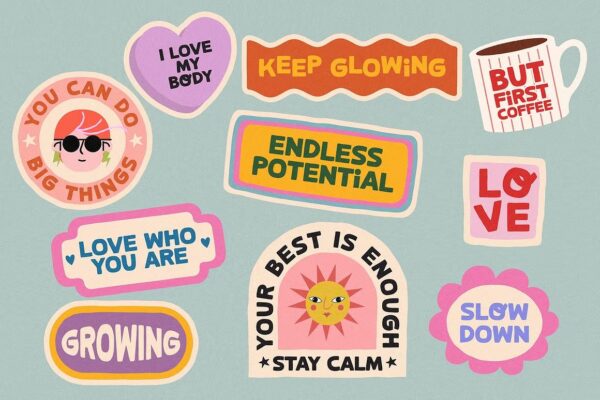
Glimmer Hood – Sans Serif Font
Glimmer Hood adalah font sans serif modern dengan tampilan elegan dan bersih. Mengusung desain huruf yang seimbang dan minimalis, font ini sangat cocok untuk branding, editorial, logo, kemasan produk, dan tampilan digital. Gaya geometrisnya menghadirkan kesan profesional, kontemporer, dan mudah dibaca dalam berbagai ukuran.
• Sans serif bergaya modern dan minimalis
• Termasuk huruf besar, kecil, angka, dan simbol